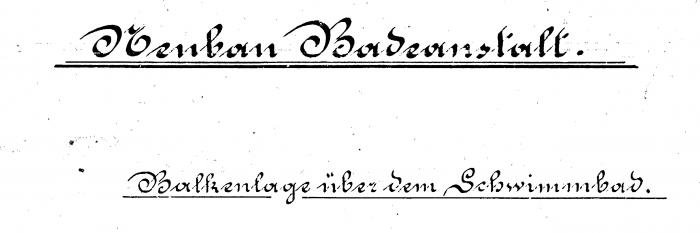
Suche Typo Ende 19. Jh.
Ich habe eigentlich nichts mit Schriften zu tun. Dennoch suche ich für ein Layout eine besondere Schrift. Auf dem Beispielbild seht ihr verschiedene Buchstaben. Ich habe schon an Sütterlin und Kurrent gedacht, aber irgendwie sind die es nicht, zumindest nicht in ihrer normalen Version.
Das war damals die gängige Schrift zum Bescxhriften von Zeichnungen - Praktisch der Vorläufer der DIN16
Ich habe eine, wenn auch etwas weniger breite Version nach alten Zeichnungen digitalisiert:
ein kleiner Ausschnitt aus ein er Pause von damals:
Da diese Schrift damals ja immer handschriftlich war, unterscxheidet sie sich von Schreiber zu Schreiber etwas, so eben das andere d in deinem Muster und uim gegensatz zur leichten Linksneigung meiner Vorlage die leichte Rechtsneigung bei deinem Muster. Auf Wunsch passe ich daserne an.
So weit mir bekannt geht die Schrift zurück auf Soenneckens Rundschrift, eine mit der Breitfeder geschriebene Variante der französische Ronde. Friedrich Soennecken hatte 1870 begonnen diese Schriftart den Mitgliedern des Kaufmännischen Vereins zu unterrichten. 1875 brachte er das erste Heft seiner Rundschrift-Methode raus. Ausschlaggebend für den Erfolg von Soenneckens Rundschrift war wohl die sehr positive Bewertung durch den Berliner Ingenieur Geheim Regierungs-Rat Professor Franz Reuleaux, Direktor der Gewerbe-Akademie in Berlin. In den nachfolgenden Jahren wurde die Rundschrift in einer Reihe von Behörden und Ministerien eingeführt. Namentlich erwähnt Soennecken auf seine Rundschrift-Hefte die Vermessung-Beamten des Königlichen Preussischen Finanz-Ministerums, sowie die Kadetten-Anstalten des Königlichen Preussischen Kriegs-Ministeriums. Auf den seit 1878 erscheinenden Muster-Zeichnungen der Königlichen Preussischen Eisenbahn wird ebenfalls konsequent Soennecken’s Rundschrift für die Beschriftung der Zeichnungen eingesetzt. In Meyers Konversationslexikon (4e Auflage, 1885-1892) stellt im Absatz »Schreibkunst« Soennecken mit seine Rundschrift sowie sein Buch Das Deutsche Schreibwesen und die Notwendigkeit seiner Reform der einzige relevante Referenz. 1879 erschien bereits die 100. Auflage einer seiner Rundschrift-Hefte. Die Rundschrift dürfte also eine große Verbreitung gehabt haben.
… Auf den seit 1878 erscheinenden Muster-Zeichnungen der Königlichen Preussischen Eisenbahn wird ebenfalls konsequent Soennecken’s Rundschrift für die Beschriftung der Zeichnungen eingesetzt. …
und genau nach diesen habe ich dann meine Schrift gezeichnet. Herzlichen Dank für diese Zusatzinfos!